타이포그래피의 독특한 상상_알리다 로지 소이어 Alida Rosie Sayer
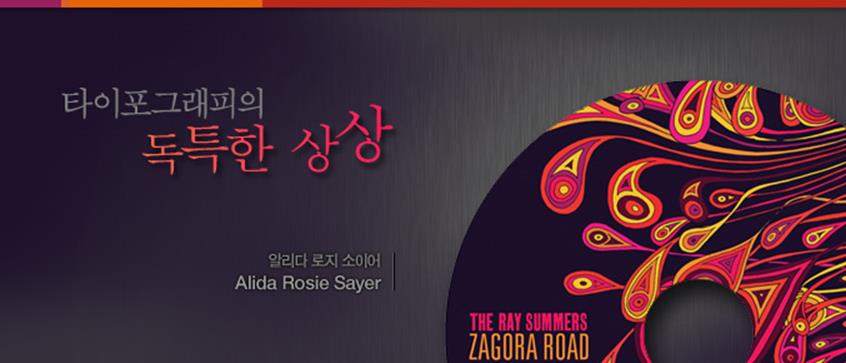
2009년 ‘D&AD Best New Blood Award’로 이름을 알리기 시작한 20대 후반의 젊은 디자이너 알리다 로지 소이어(Alida Rosie Sayer). 시각디자인 전반에 걸쳐 다양한 작업을 보여주고 있는 그는 특히 독특한 타이포그래피 디자인으로 두드러진 활동을 펼치고 있다. 지금까지 그가 해왔던 일련의 작품들을 살펴보면 3D로 표현한 타이포그래피라던지, 영상과 결합한 타이포그래피 애니메이션 등 그가 자신의 아이디어를 발현하기 위해 상당히 많은 실험적 노력을 해왔다는 것을 알 수 있다.
그래서인지 그의 작업들을 살펴보면 상당수가 한눈에도 호기심과 흥미를 불러일으키는 작품들로 구성되어 있다. 또한 알리다 로지 소이어 스스로도 이런 독특한 아이디어가 그의 앞으로의 작업에도 디자인 소스가 될 것이라 하니, 다음에는 어떤 변칙된 디자인으로 보는 이들의 흥미를 이끌어 낼 것인지 그의 활동에 꾸준한 관심을 가져보는 것도 좋을 듯 하다.
국내 독자들에게 간단한 자기소개 부탁드립니다.
글래스고 예술학교에서 건축과 일러스트레이션을 전공하고 현재 런던에서 프리랜서로 활동하고 있는 시각디자이너입니다. 주로 타이포그래피 디자인을 다루고 있고, 3D 디자인, 애니메이션, 일러스트레이션, 뮤직아트워크, 패션 브랜딩, 영상 타이틀 등 시각디자인 전반 다양한 분야의 프로젝트들도 시도하고 있습니다.
디자이너가 된 계기와 그 과정에 대해 말씀해주신다면
어릴 때부터 지금까지 항상 무언가 만들거나 그리고 싶은 충동을 가지고 있습니다. 그리고 그것을 표출하기 시작하면서 자연스럽게 디자이너의 길로 들어서게 된 것 같습니다. 디자인을 공부하기 위해 들어간 글래스고 예술학교에서 처음 선택한 전공은 건축이었지만, 이내 곧 일러스트레이션으로 전공을 옮겼습니다. 제가 갖춘 능력 안에서는 일러스트레이션이 상상력을 표현하는데 있어, 그 자유의 폭이 더욱 크다고 생각했기 때문이죠. 생각하고, 배우고, 그려내고 하는 과정 하나하나가 디자이너가 되는 일련의 과정의 요소들이라고 볼 수 있습니다.
프로젝트들 중에서 3D타이포그래피 작업들이 눈에 띄는데, 3D타이포그래피를 작업하시는 특별한 이유가 있나요? 어떻게 만드는 것인지 역시 궁금합니다.
하나의 정보를 담은 평면이 켜를 쌓아 서로 소통하는 비주얼적인 형상을 표현하는데 흥미를 가지고 있습니다. 이것이 종종 3D로 표현되는 것이죠. 주로 이런 작업은 반투명한 재질을 사용한 솔리드한 평면들을 쌓은 후 그것을 다시 깎아내어 시각적으로 평범하지 않은 깊이감을 만들어내는 방식으로 이뤄집니다.
3D로 타이포그래피를 표현하는 것은 표식으로써 인식되는 문자의 존재 자체를 강조하는 것 뿐만 아니라 깊이와 밀도를 가진 추상적인 비주얼 형상으로 새로운 ‘읽기’의 경험을 하고자 하는 의도입니다. 이것은 언어를 이해하고 해석하는 방법의 변형으로 문자가 가진 무한한 가능성 중 하나를 말하고자 한 것입니다.
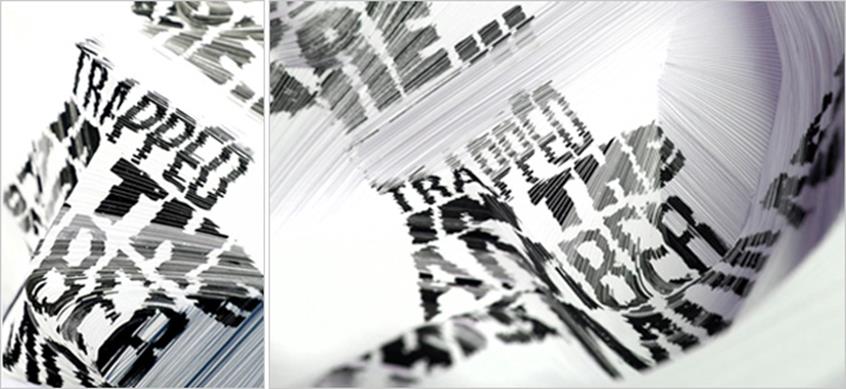
▲ Here we are(2010), hand-cut screen prints on cartridge paper, photo © Philip Sayer 알리다 로지 소이어의 3D타이포그래피 프로젝트 ‘제5도살장’ 시리즈
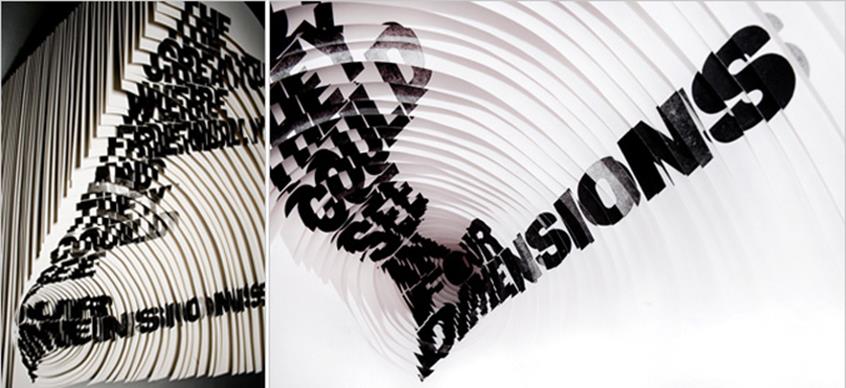
▲ The creatures were friendly(2009), 알리다 로지 소이어의 3D타이포그래피 프로젝트 ‘제5도살장’ 시리즈
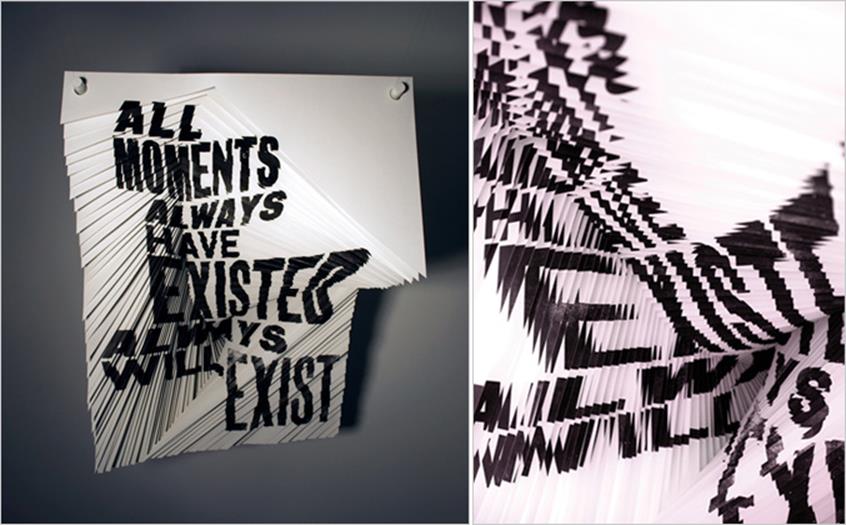
▲ All moments(2009), 알리다 로지 소이어의 3D타이포그래피 프로젝트 ‘제5도살장’ 시리즈
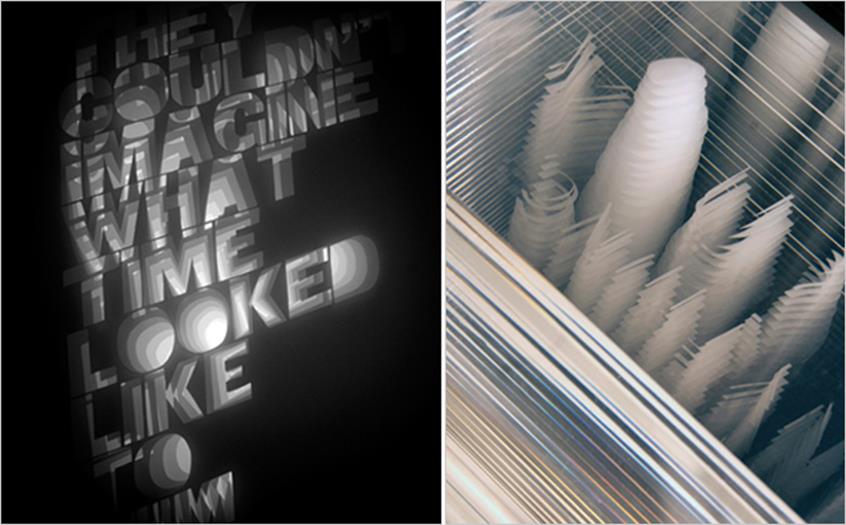
▲ They couldn’t imagine(2009,좌), Why anything?(2010,우), 알리다 로지 소이어의 3D타이포그래피 프로젝트 ‘제5도살장’ 시리즈
그렇다면 3D타이포그래피가 대표 프로젝트라고 볼 수 있나요? 아니면 스스로 생각하는 대표작이 따로 있는지 궁금합니다.
네. 그렇다고 볼 수 있습니다. 특히 개인적으로는 커트 보네거트((Kurt Vonnegut)의 소설 ‘제5도살장(Slaughterhouse Five)’에서 영감을 받은 일련의 3D 작업 시리즈를 대표작으로 뽑을 수 있습니다. 이 ‘제5도살장’ 시리즈에는 그 동안 제가 추구했던 많은 디자인 아이디어들이 함축되어 표현되어 있는 동시에 앞으로 만들어낼 작업에 대한 소스이기도 하기 때문이죠.
‘제5도살장’은 저자가 직접 겪었던 2차 대전 당시 독일의 대규모 수용소 시설에서의 경험을 소설화 한 것으로 시공간이 뒤죽박죽 엉킨 정신분열성 소설입니다. 이 책을 처음 읽었을 때, 보네거트가 어떤 식으로 소설의 내용을 독자들의 머리 속에 집어넣으려고 했는지에 대한 상상에 사로잡혔고, 시공간을 초월한 소설의 구성이나 비현실적 컨셉, 등장인물의 기이한 비주얼에 대한 묘사 등 소설에 대한 저만의 느낌이 이 3D 작업물로 시각화 된 것입니다.
이 작품들로 작년에 전시를 열기도 했습니다. ‘There is no why’라는 타이틀로 런던의 갤러리 우(Gallery Woo)에서 열렸던 제 첫 번째 개인전이었죠. 그래서 이 작업들을 ‘There is no why’시리즈라고 부르기도 합니다.
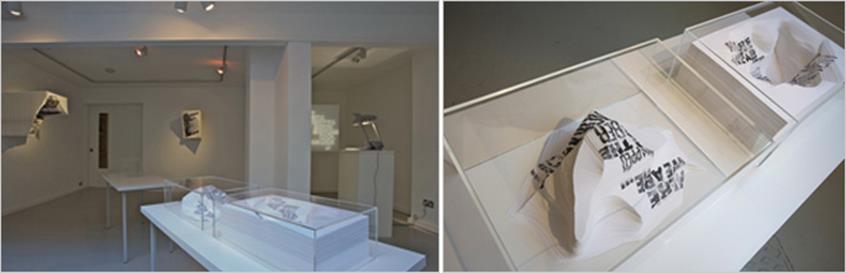
▲ 런던 갤러리 우(Woo)에서 열렸던 ‘There is no why'(2010) 전시 모습
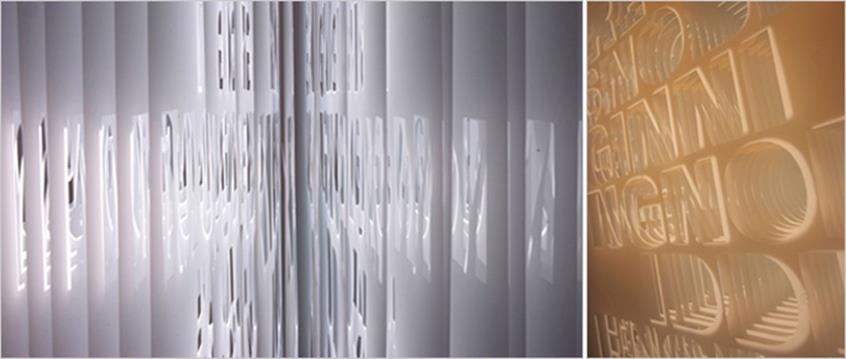
▲ There is no beginning, detail (2010), photo © Philip Sayer. There is no why’에서 선보인 또 다른 3D 타이포그래피 작품
전체적으로 작업들에서 유독 블랙과 화이트 컬러를 자주 볼 수 있는데, 혹시 선호하는 컬러가 따로 있는 것인가요?
선호한다기 보다 블랙과 화이트, 무채색의 감각은 본능적으로 익히고 있는 것 같습니다. 이것은 아버지 필립 소이어(Philip Sayer)의 영향이라고 생각합니다. 필립은 흑백사진 작가로 어릴 때부터 컬러 이전의 이미지의 톤과 형태에 대해 인식할 수 있도록 도와주었습니다.
홈페이지를 보면 ‘Suspiria’ 영상이 상당히 흥미로운데, 어떤 프로젝트인가요?
‘서스피리아(Suspiria)는 1972년 제작된 다리오 아르젠토(Dario Argento) 감독의 이탈리아 컬트 호러 영화입니다. 홈페이지의 영상 작품은 이 영화를 보고 제가 만들어본 타이틀 시퀀스입니다. 영화의 오리지널 사운드 트랙인 고블린(Goblin)의 사이스(Sighs)를 배경음악으로 손수 직접 그린 타이포그래피 프레임과 디지털 애니메이션으로 영상과 음악, 타이포그래피의 결합을 표현하려 했던 작품입니다. 이 같은 영상 타이틀 작업은 제가 최근 흥미를 가지고 있는 분야이기도 합니다.
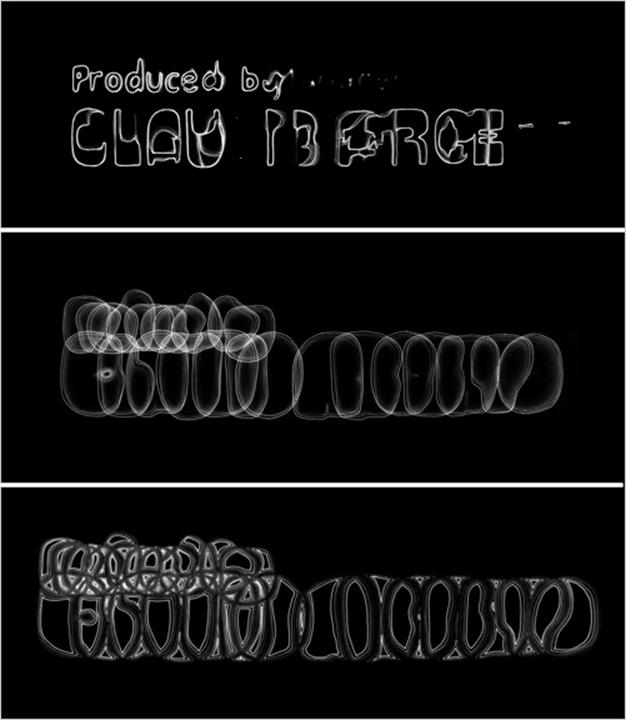
◀ Suspiria Title Sequence still(2009)
▲ Suspiria Title Sequence still(2009)
디자인적 영감이나 힌트는 주로 어디에서 발견하나요?
어디서든지요. 그릴 수 있는 펜과 종이가 있다면 언제든지 좋은 아이디어를 만들 수 있습니다.
자신만의 디자인 철학을 가지고 있나요?
네. ‘편견을 갖지 말자’입니다.
자신에게 영향을 끼쳤거나 선호하시는 디자이너가 있다면
우선 아버지 필립의 사진은 어릴 때부터 많은 영향을 주었습니다. 사진 자체뿐 아니라 출판물이나 포스터 속에서 다른 디자이너들이 필립의 사진들을 어떻게 편집하고 사용하는지를 접할 수 있었죠. 이때 앨런 키칭(Alan Kitching), 토마스 헤더윅(Thomas Heatherwick), 폴 랜드(Paul Rand), 토르트 본체(Tord Boontje)등의 디자이너들을 알게 되었고, 그들의 디자인에서도 많은 영향을 받았습니다. 또한 코넬리아 파커(Cornelia Parker)나 올라퍼 엘리아슨(Olafur Eliasson), 스티브 맥퀸(Steve McQueen)과 같은 아티스트들의 작업도 좋아합니다. 스테판 사그마이스터(Stefan Sagmeister)의 실험적인 타이포그래피 디자인도요.
앞으로의 계획이 있다면
정해진 계획이라기보다 기회가 주어진다면 거대한 스케일의 타이포그래피 설치물을 제작해보려 합니다. 사람들이 내,외부를 돌아다니며 직접적으로 경험할 수 있고, 환경친화적인 성격을 갖춘 타이포그래피를 표현하는 싶은 것이죠. 또한 서스피리아 같은 타이포그래피를 이용한 영상 타이틀 작업도 계속 이어나갈 생각입니다. 상당히 흥미로운 작업이거든요. 두 가지 이상의 언어를 가지고 작업하는 것도 재밌을 것 같습니다. 서로 전혀 다른 문자들이 공존하며 만들어지는 타이포그래피 디자인은 저에게 새로운 도전이 될 것입니다.
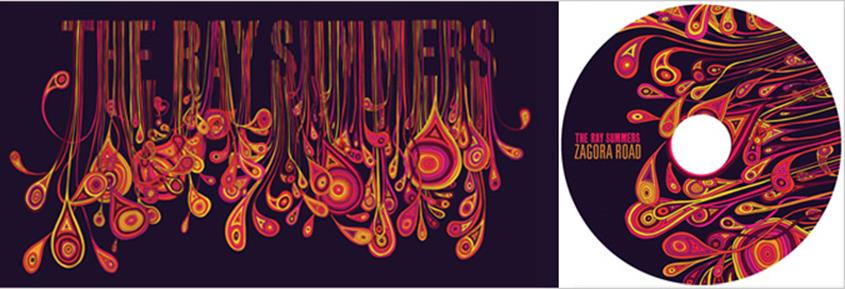
▲ Zagora Road single artwork(2009)
▲ Heshka Rashka single(2010)
▲ Fuse(2010, 좌), Never Say Clever album(2010, 우)